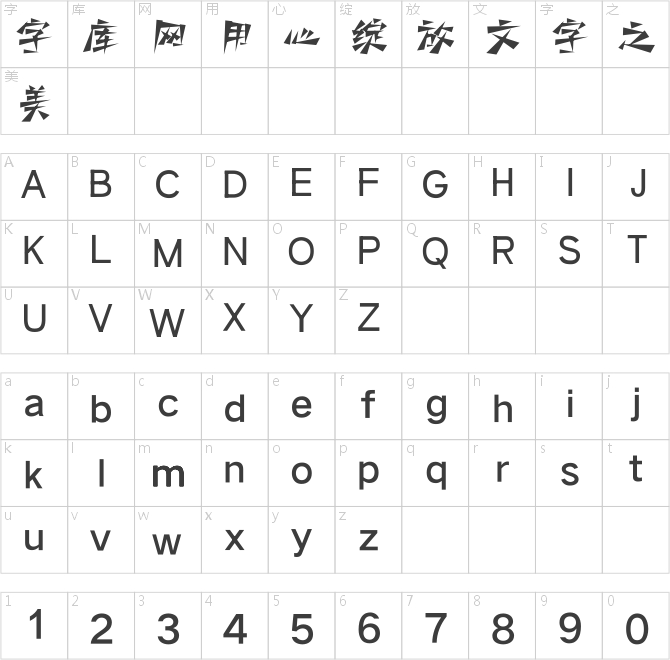
字体名称: 三极尖叫体
三极尖叫体
三极尖叫体介绍
三极尖叫体笔画设计为直线、斜线既有方向性又有力度的三角形图形,挺拔、有力等形式心里特征,尖锐而收费自如,创意卓越,个性突出。易于识别,便于应用。
三极尖叫体字体SJjianjiao-Regular字库是一款让人赏心悦目、百看不厌的中文字体,适合各类广告和产品包装设计应用,字体大小1.44MB,格式为ttf字体,上传用户是三极字库,作者/版权方为三极字库/欧伟